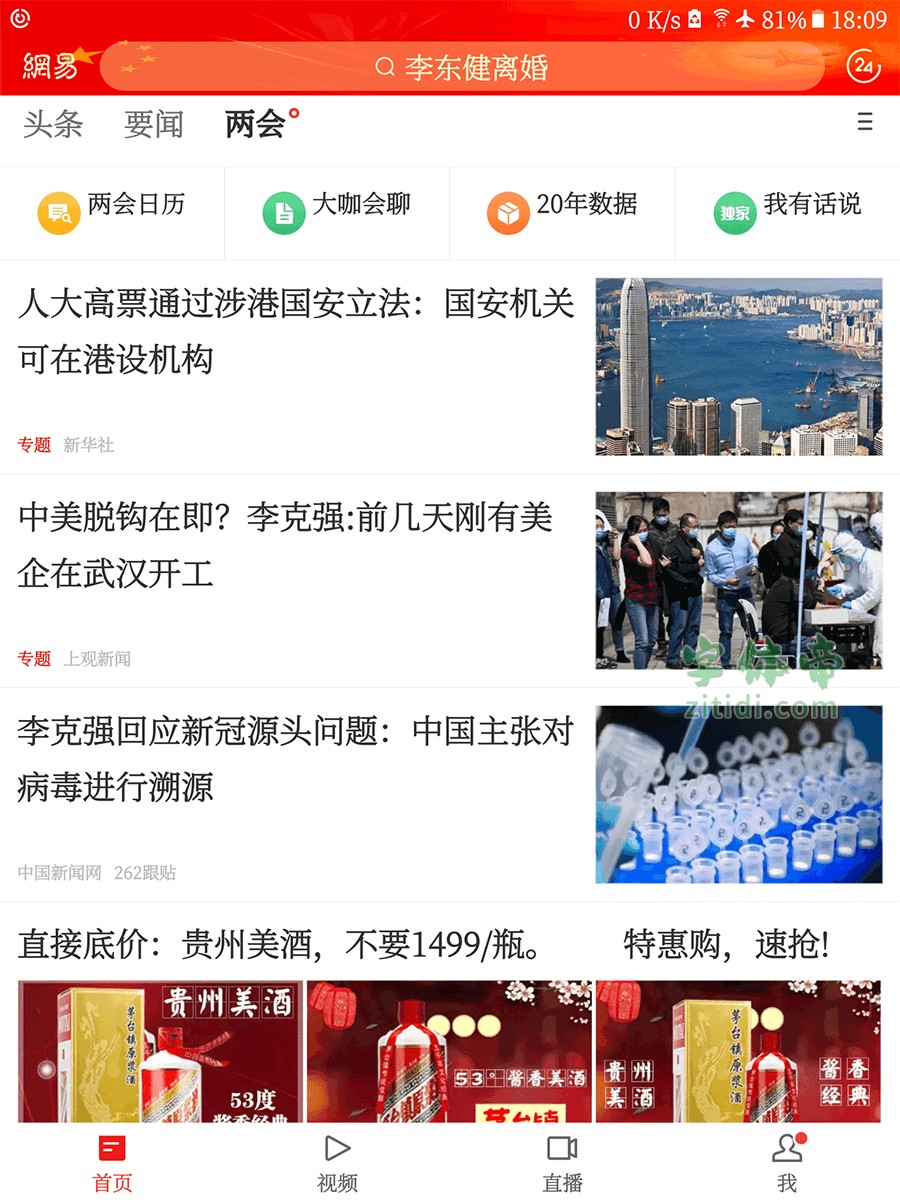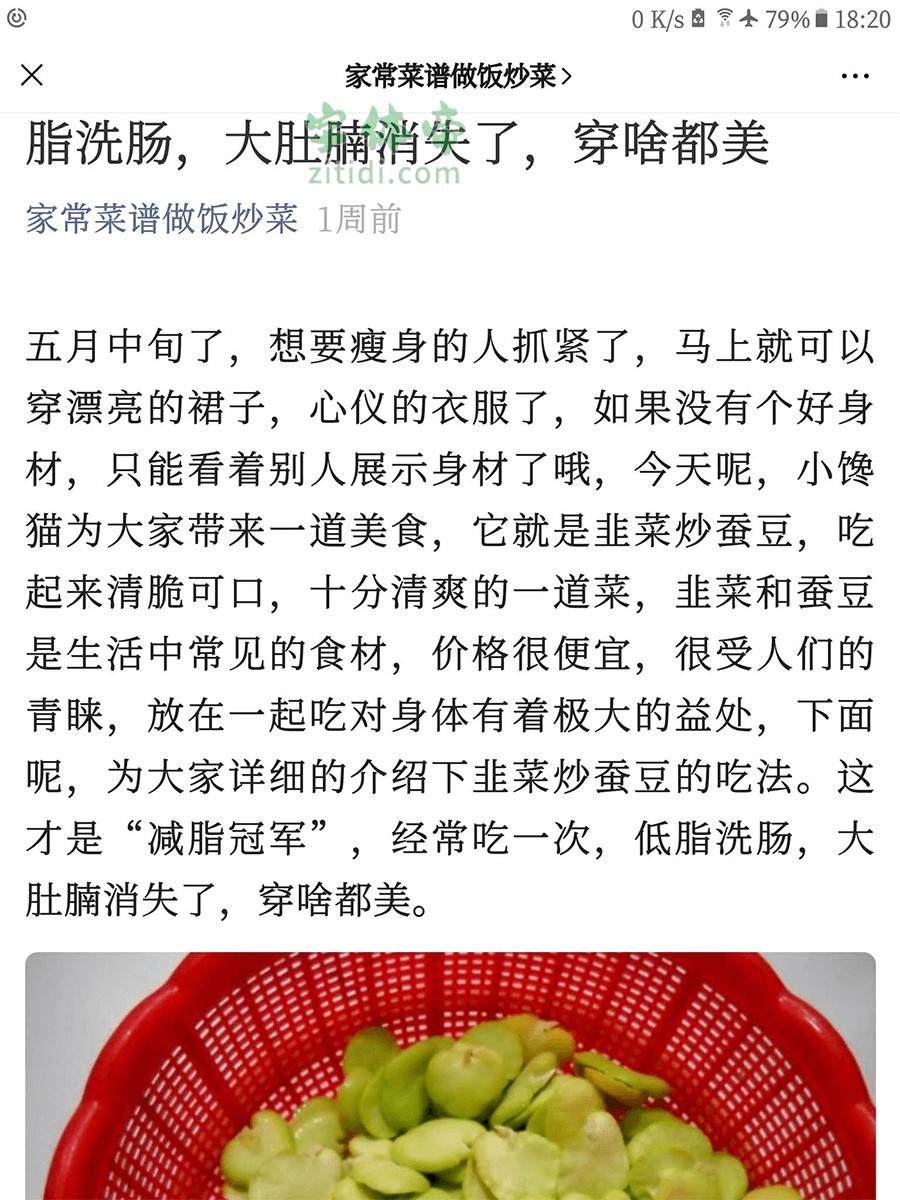
极限社区的chncwk同学连续30天的超长假期,被宅在家里,百无聊赖之际把思源屏显宋GB2312内的汉字筛选了几遍,修复了肉眼可见的笔画破损问题。另外重订了西文字母的衬线,让其回归较传统的风格,更易与汉字融合;再用极其变态的流程甄选了300多字的字形用于本项目的优化。因页面观感比起原字体有了较为明显的变化(硬朗→圆熟),故更名做全新发布,避免喜欢原风格的人被覆盖。
这款字体可以用于手机替换字体(非直接替换,可能需要特定的转码工具,部分软件支持直接安装),看上去会比较复古清爽,效果挺不错的。